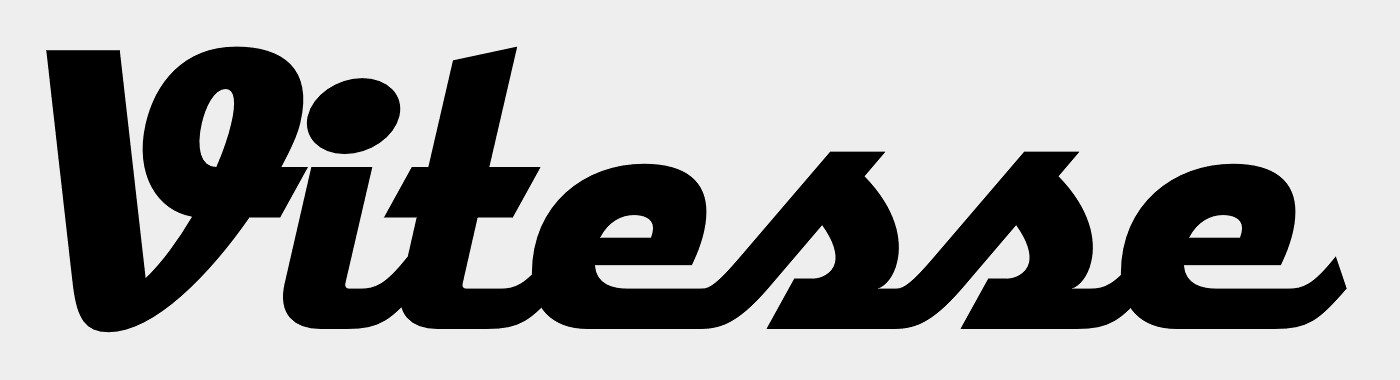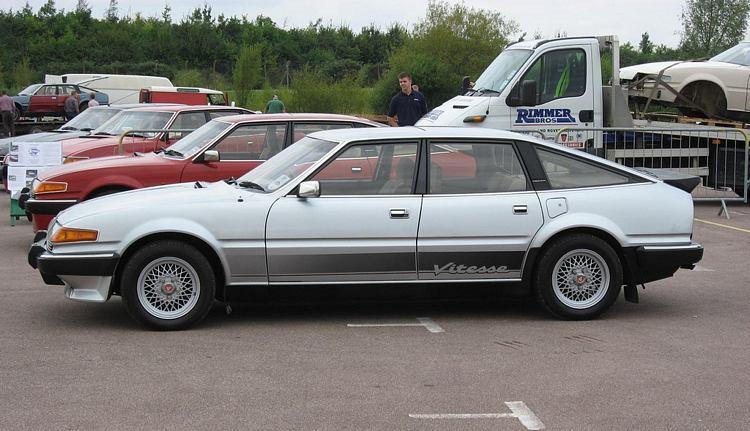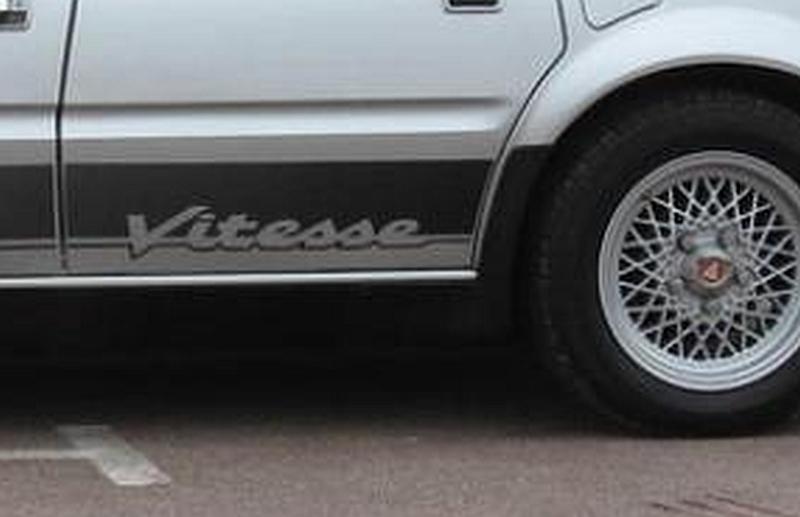
Schriftart Rover Vitesse SD1
Ich hoffe jetzt mal auf die Hilfe von den "Schriftarten Cracks" :-) nachdem ich selber nicht mehr weiterkomme und nun Profi Hilfe benötige.
Ich bin auf der Suche nach einer, meiner Meinung nach, Schriftart aus den 80'ern.
Es handelt sich um den seitlichen Aufkleber eines Auto's.
Ein Rover SD1 Sportversion Vitesse.
Hallo SD1, bin selber auf der Suche nach der Schrift für "Vitesse" bzw. nach einer Bezugsquelle. Bisher nicht fündig geworden. Bist Du weiter? Grüsse. Polo
Hallo Norbert p hast du auch eine vitesse ?